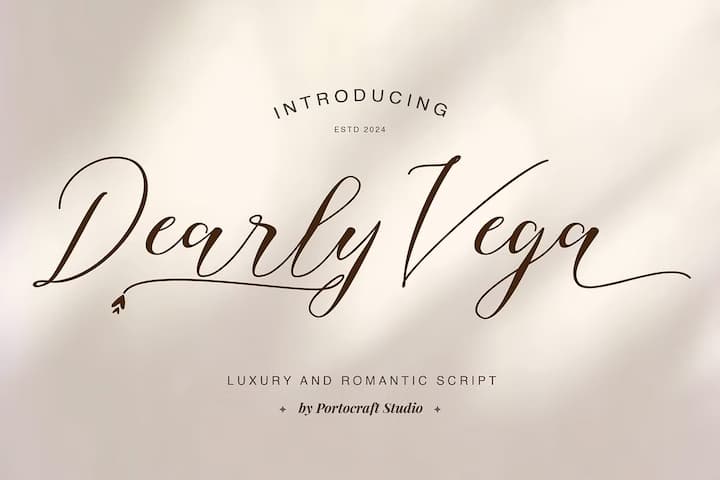
Dearly Vega
本日は七夕という事でこちら。織姫ことベガ(こと座一等星)の名を持つモダンカリグラフィースクリプト。よくあるスタイルの書体だが、他に比べてややコントラストが強くグリフもかっちり目だろうか。大文字にはオルタネートがないが小文字には大量にあり、中には画像のようにスワッシュの先にハートのような飾りが付いたものがある。リガチャーも20種ほど。1ウェイトのみ。